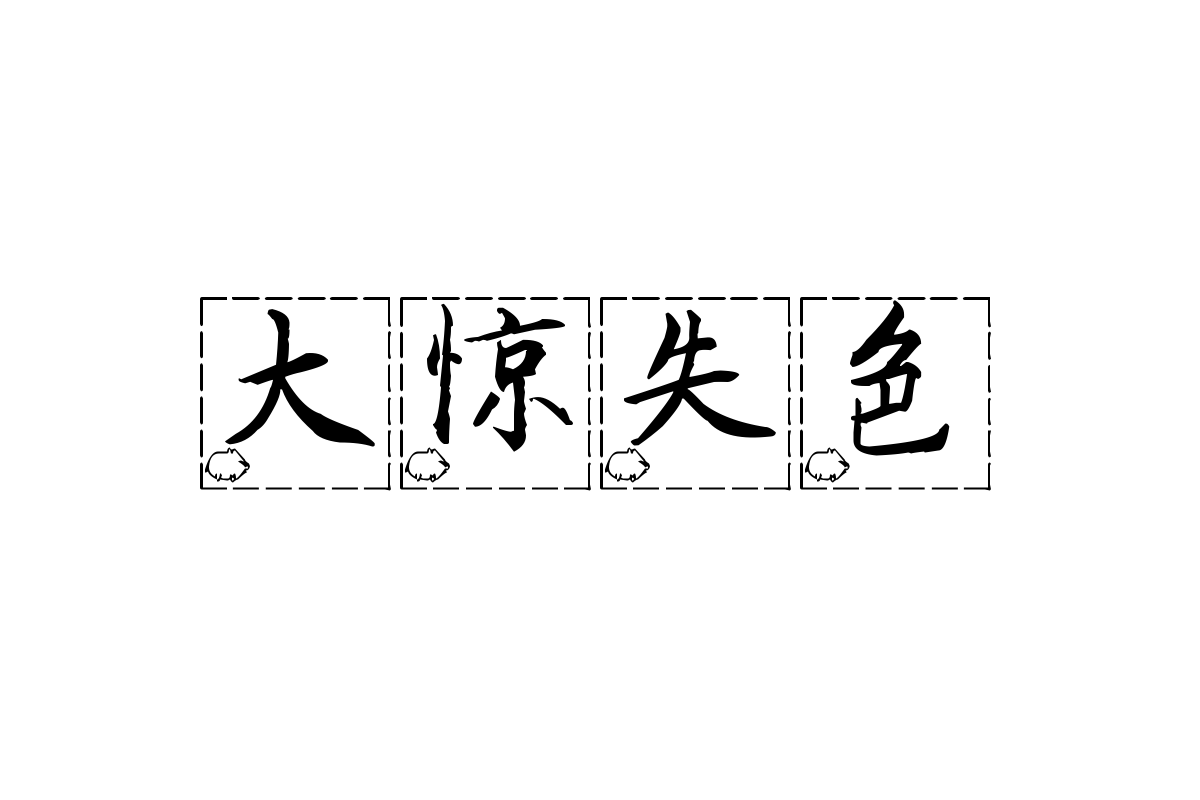
汉呈魅力格子字体是一种具有独特魅力的中文字体,它采用了传统的格子设计,使得文字看起来更加美观大方。这种字体的特点是笔画粗细分明,字形结构紧凑,给人一种简洁明快的感觉。同时,它还具有一定的艺术感,能够很好地表达出作者的情感和个性。
汉呈魅力格子字体适用于各种需要使用中文的文字场合,如广告、书籍、报纸、杂志等。它的应用范围广泛,可以满足不同用户的需求。无论是用于商业宣传还是个人创作,汉呈魅力格子字体都能够展现出其独特的魅力,让人印象深刻。